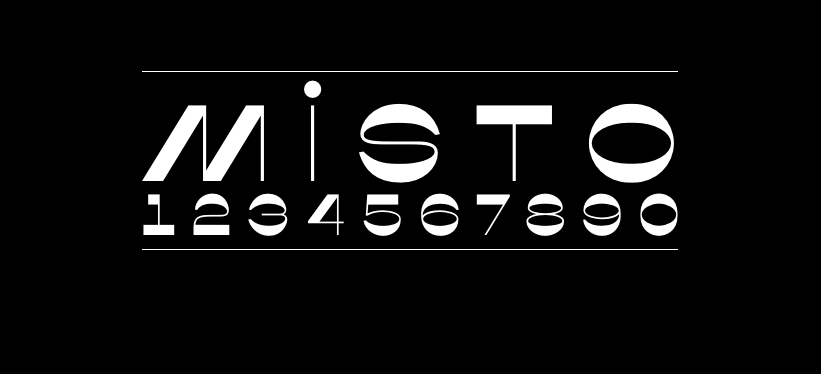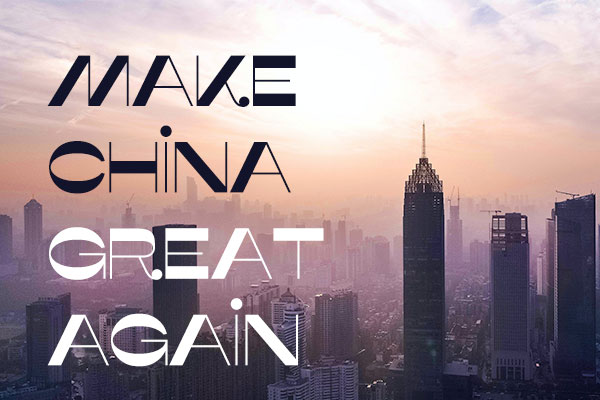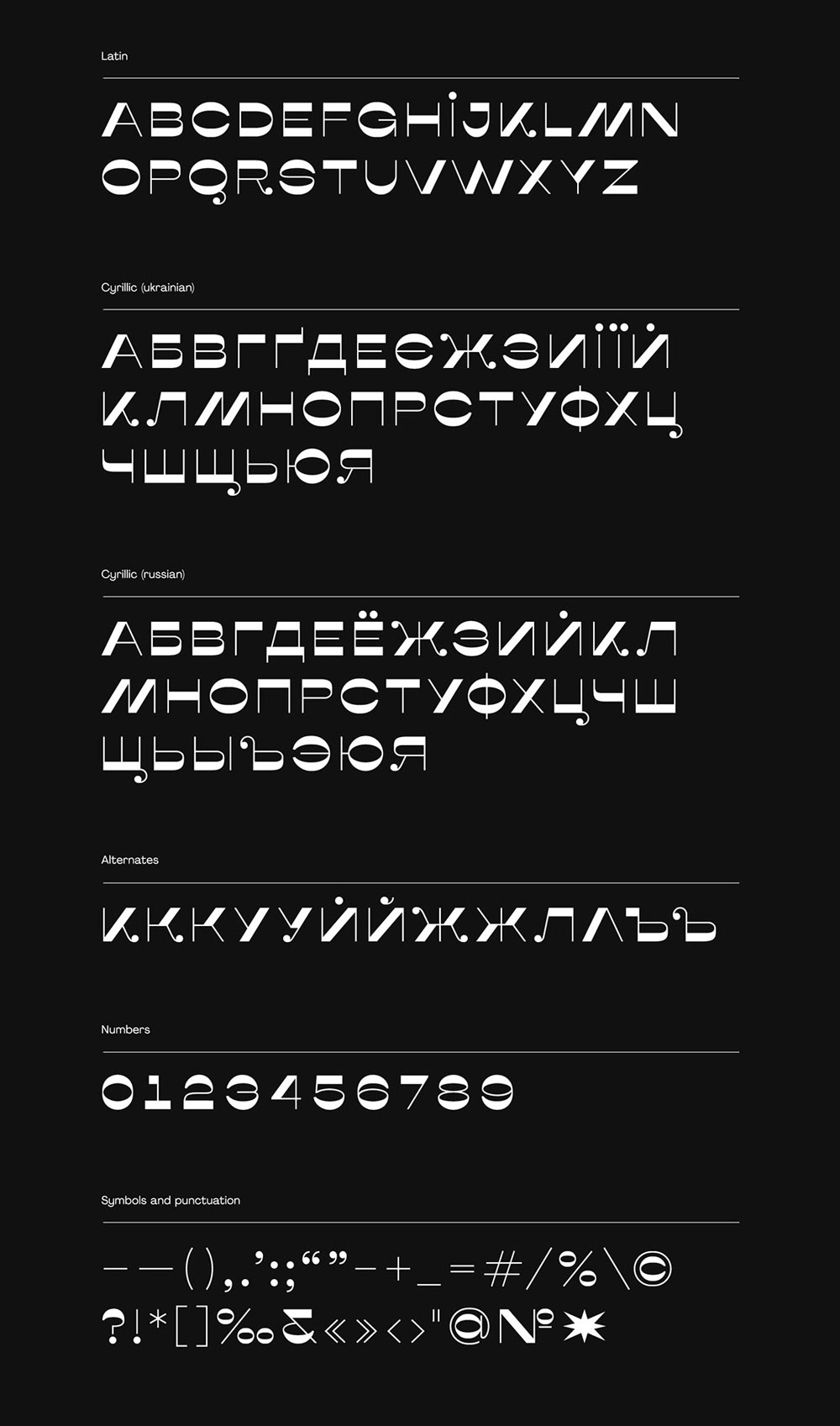
Misto
Misto是一种免费的反对比度显示字体,作者是来自乌克兰的Katerina Korolevtseva,其设计灵感来自切尔诺贝利爆炸后出生的乌克兰最年轻的城市Slavutych。
Misto字体设计用于标题,包括徽标设计,品牌标识,网站,包装和海报,效果最好。它同时支持西里尔文和拉丁文版本。